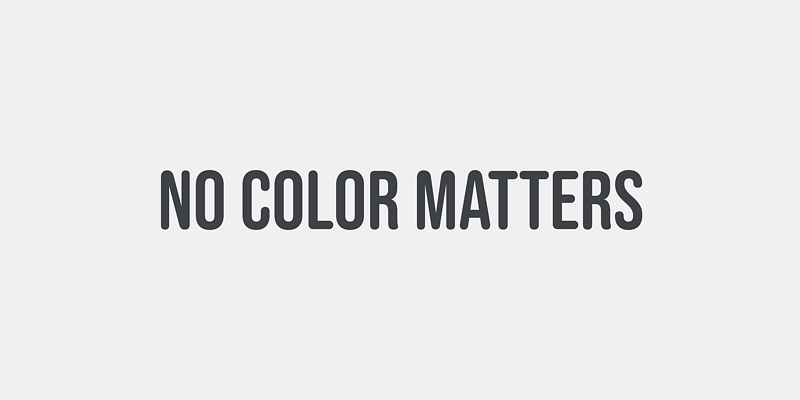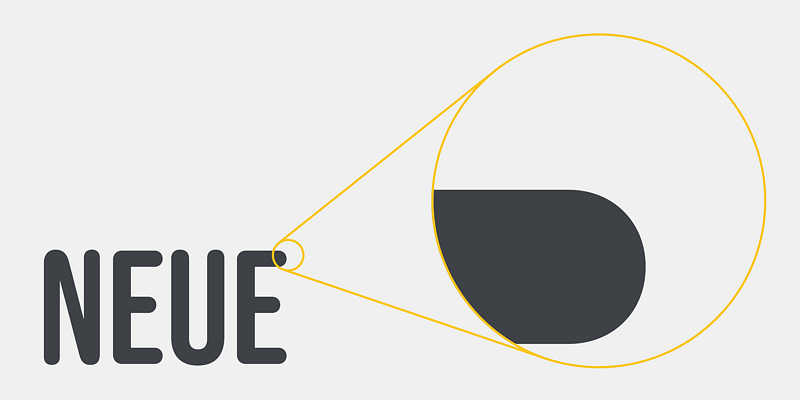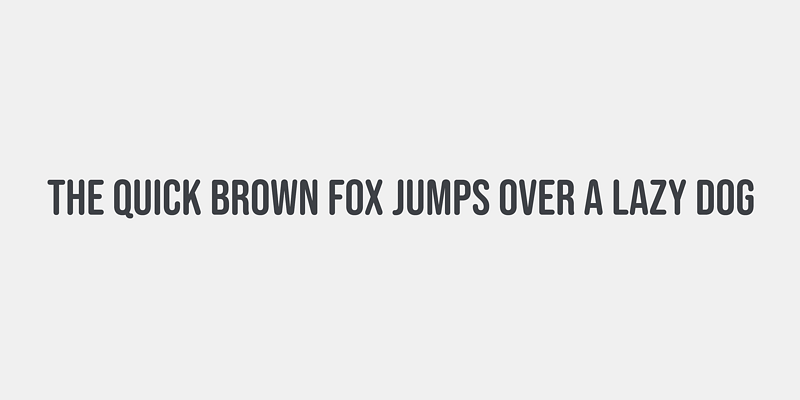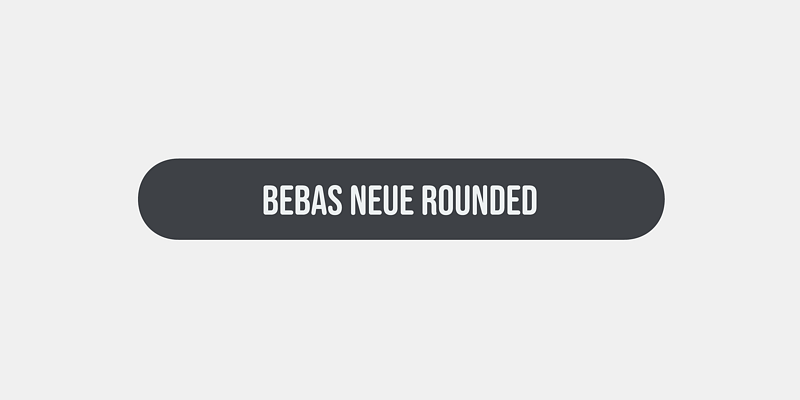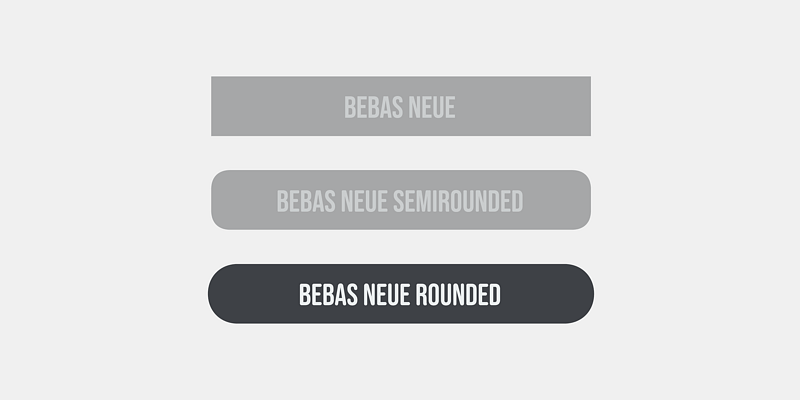
Bebas Neue Rounded ist die Bebas Neue mit abgerundeten Ecken und Enden. Die grundlegende Theorie und die Proportionen sind dieselben wie bei Bebas Neue, aber die abgerundete Form vermittelt einen warmen, weichen und natürlichen Eindruck.